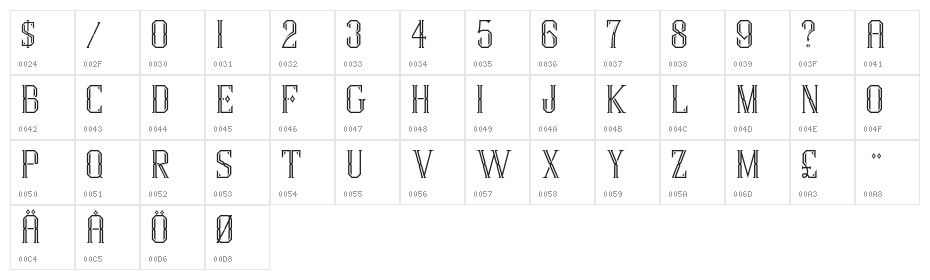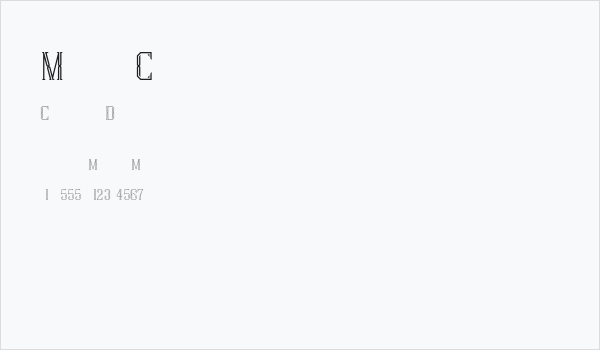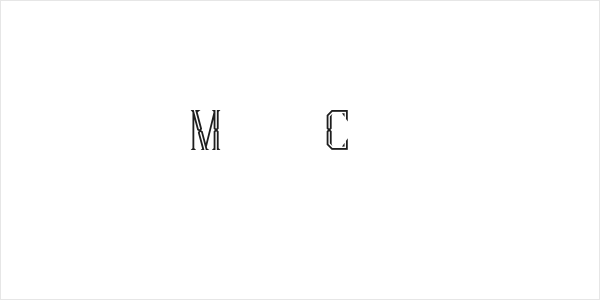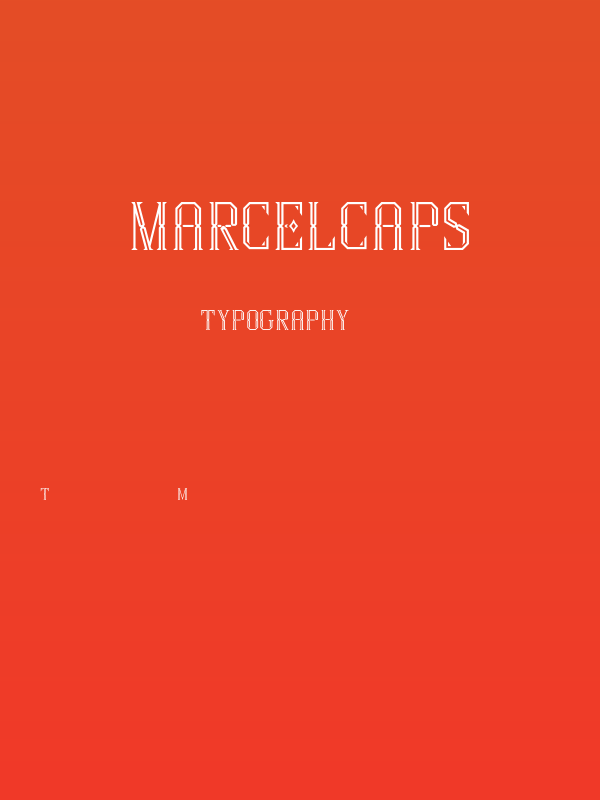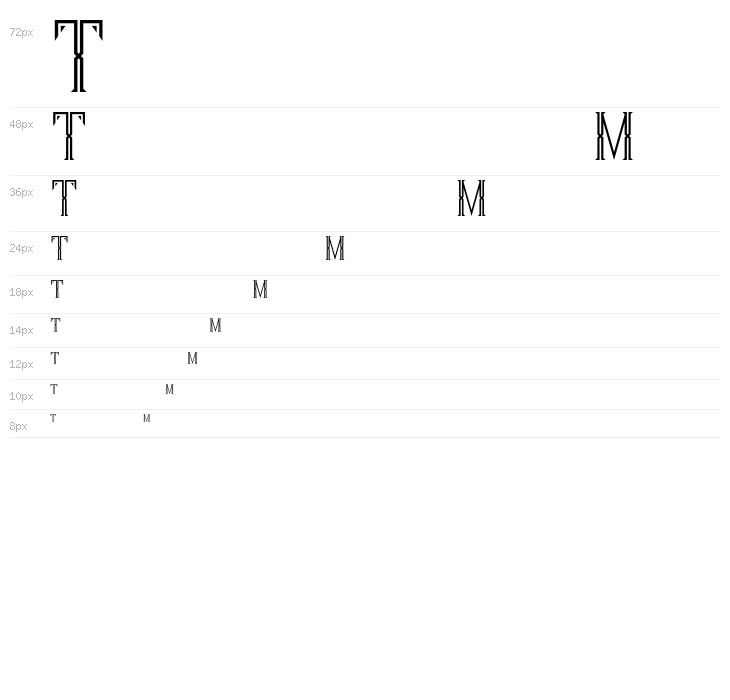
MarcelCaps Font
| Kategorien | Retro |
| Gesamtstil | Vintage |
| Anwendungsfall | Headlines, Logos, Decorative elements |
| Vorgeschlagene Projekte | Ideal for vintage-themed posters, branding, logos, and decorative headlines. |